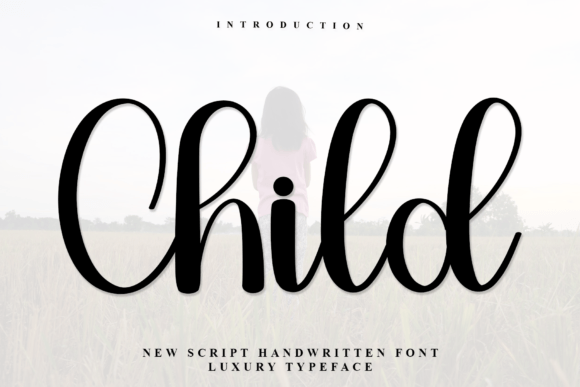
Child
Child : la police manuscrite qui allie fraîcheur et élégance décontractée
Vous cherchez une typographie handwritten qui respire la légèreté tout en conservant une élégance naturelle ? Child est la réponse idéale. Conçue avec des strokes fluides et des lignes organiques, cette police apporte une touche chaleureuse à tous vos projets créatifs.
Voici pourquoi Child séduit les designers, les marketeurs et les créateurs de contenu :
- Aspect rafraîchissant : Les courbes douces et les traits spontanés donnent l’impression d’une écriture à la main, idéale pour créer une connexion authentique avec votre audience.
- Versatilité exceptionnelle : Que ce soit pour du branding, des invitations personnalisées, des publications sur les réseaux sociaux ou des supports imprimés, Child s’adapte parfaitement à chaque contexte.
- Lisibilité optimisée : Malgré son style manuscrit, la police reste claire et lisible, même en petite taille, ce qui la rend fonctionnelle pour les titres comme pour le corps de texte.
- Personnalité chaleureuse : L’aspect détendu de Child insuffle une vibe « laid‑back », parfaite pour les marques qui veulent paraître accessibles et proches de leurs clients.